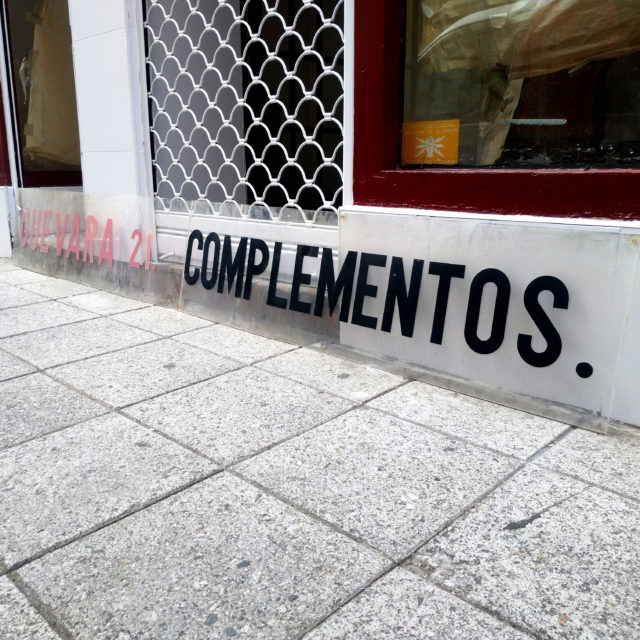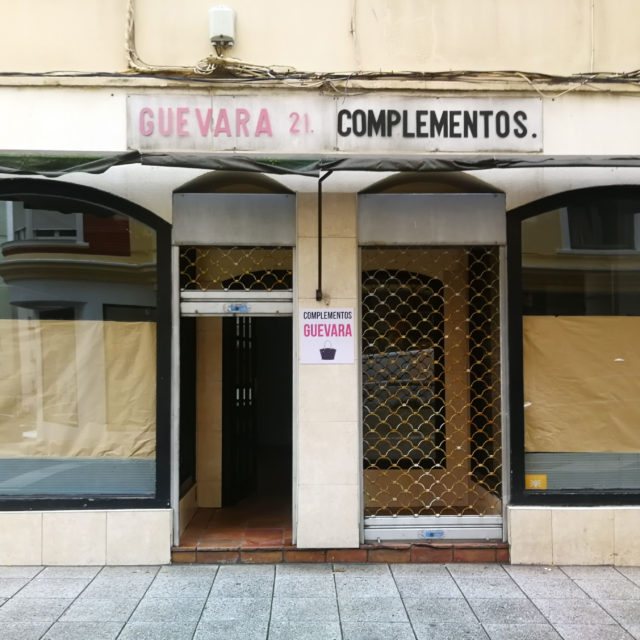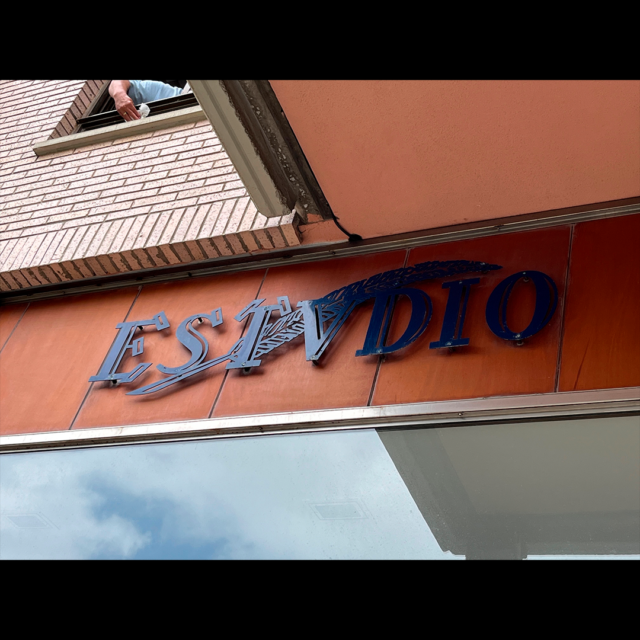
Salvados Libreria Estvdio y Guevara, 21 Complementos
Iniciamos el nuevo curso con la incorporación de dos nuevos rótulos al Archivo de Santatipo. Gracias a la colaboración y sensibilización colectiva, se han podido salvar de su desaparición los rótulos de:
• Libreria Estvdio (Avenida de los Castros, Santander)
• «Guevara, 21» Complementos (Santander)
El de la Libreria Estvdio ha sido salvado gracias a Ángel, nuevo propietario de lo local, que nos avisó del inicio de la reforma y que nos guardaba las icónicas letras. Ha sido recientemente cuando hemos podido ir a recogerlas.
La Libreria Estvdio, ha sido una de las grandes librerias de Cantabria. Fundada en 1947 por Dionisio García-Barredo, abrió la pequeña librería en Calvo Sotelo, justo donde hoy estaba “Calzados Ángel”. En los años 60 ese local se amplia y no es hasta finales de los años 70 que se abre el de la calle Burgos, cerrado en 2021. Posteriormente en los años 90 abrieron una en Valle Real que cerraría en 2018. Y ya en los años 2000 abrieron otras librerías en la Avenida de los Castros, Corrales de Buelna y Muriedas, todas ya cerradas tras el cese de negocio que se anunció en 2019. Durante todo ese tiempo fue una de las librerias de referencia, con su editorial propia y el volumen de actividades culturales que se hacían.
El diseño de “Estvdio” ha permanecido intacto desde que se abrió el negocio y fue creado por el arquitecto Ricardo Sainz Martínez (quien proyectó los Jardines de Piquío) como regalo para la librería. El detalle de la “V” fue un toque personal del arquitecto.
Sobre «Guevara, 21» Complementos, fue una pequeña tienda, en un local con una fachada muy reconocible en la zona. Su salvamento ha sido gracias a Cantabristas, quienes al adquirir el local para abrir su sede social y conocedores del proyecto, nos avisaron de que bajaban el cartel y le guardaban.
Desde Santatipo, estamos encantados de que se comience a preservar nuestro #PatrimonioGráfico colectivamente. Es un gran paso para salvaguardar esa otra memoria de nuestras calles.